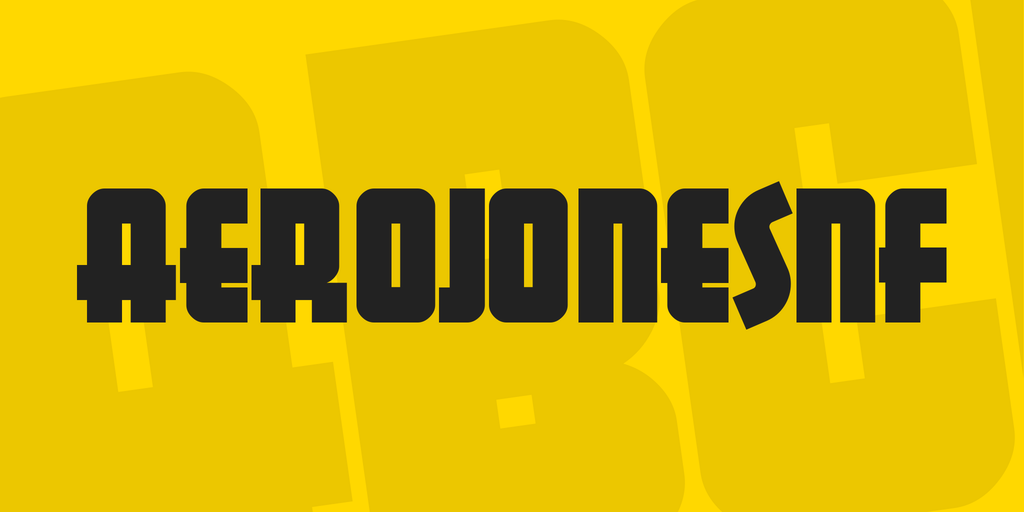
Esta fonte de exibição é uma criação inspirada no design da letra do aviso para a Italo Oil lançado em 1993 por George Guillermaz. Inspirada na simplicidade e agressividade da Huxley Vertical, mas com um peso muito maior, oferece características chamativas que se destacam quando usadas em grandes tamanhos de texto. Sua elegante tipografia moderna e vigorosa foi nomeada para enfatizar seus pontos mais interessantes. A fonte “AerojonesNF” é uma excelente opção para criações de design gráfico exuberantes e imponentes, mantendo o estilo clean e atraente do design da Italo Oil. Se você busca um design robusto que destaque sua obra como se fosse parte de um conjunto híbrido entre rock clássico e arte contemporânea, esta fonte é certamente o caminho para você.